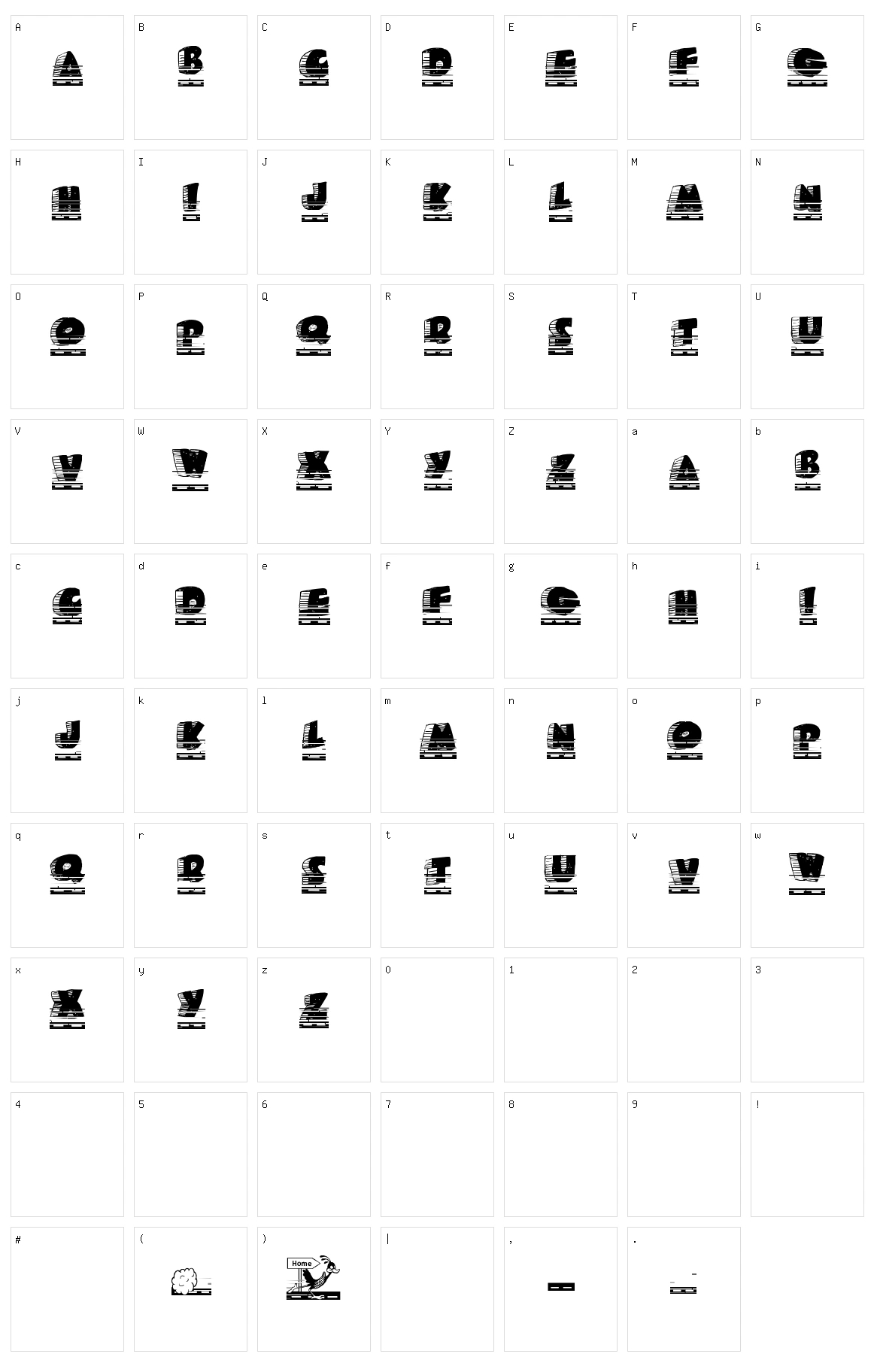
Ich habe eine ähnliche Schrift für eine Fontfreundin gemacht. Mir hat die Schrift sehr
gut gefallen, außerdem war sie sehr aufwendig zumachen, so dass ein wenig Herzblut an
ihr hängt. Deshalb bin ich froh, dass meine Fontfreundin mir erlaubt hat, diese Schrift
mit einem anderen Roadrunner noch einmal zu machen.
Für die Buchstaben habe ich das wundervolle Freewarefont Caveman von Ben Balvanz genommen.